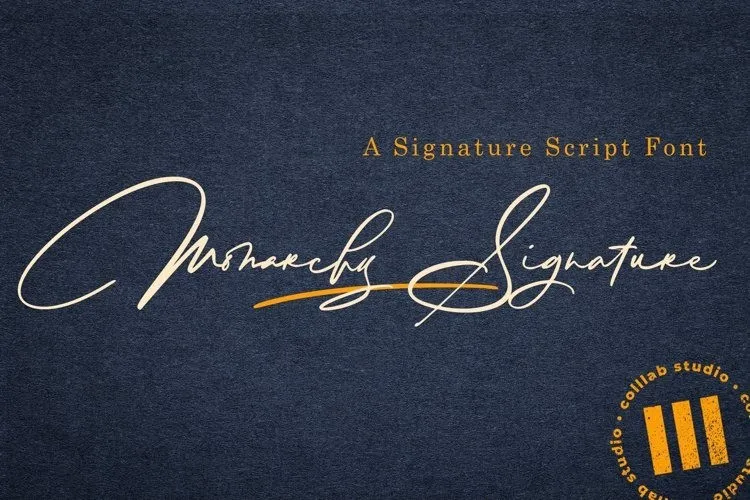
Monarchy Handwritten Font – Download Grátis
Monarchy Handwritten Font é uma elegante fonte script que transmite sentimentos refinados sem perder a modernidade. Suave e autêntico ao mesmo tempo, este tipo de escrita se destaca por sua elegância singular. Foi criado e compartilhado pela Colllab Studio, um designer atento aos detalhes que produziu uma fonte script estilosa e incrivelmente delicada. Monarchy Handwritten Font é perfeito para adicionar um toque autêntico em design como cartas de casamento, cartões de agradecimento, declarações e até mesmo logotipos. Suas linhas suaves e seus detalhes meticulosamente trabalhados fazem dela uma escolha ideal para qualquer projeto que precisa de um toque humano. Esta fonte é especialmente versátil, sendo perfeita tanto para cartões quanto para aplicativos comerciais ou outras criações gráficas em busca de um olhar pessoal e autêntico.